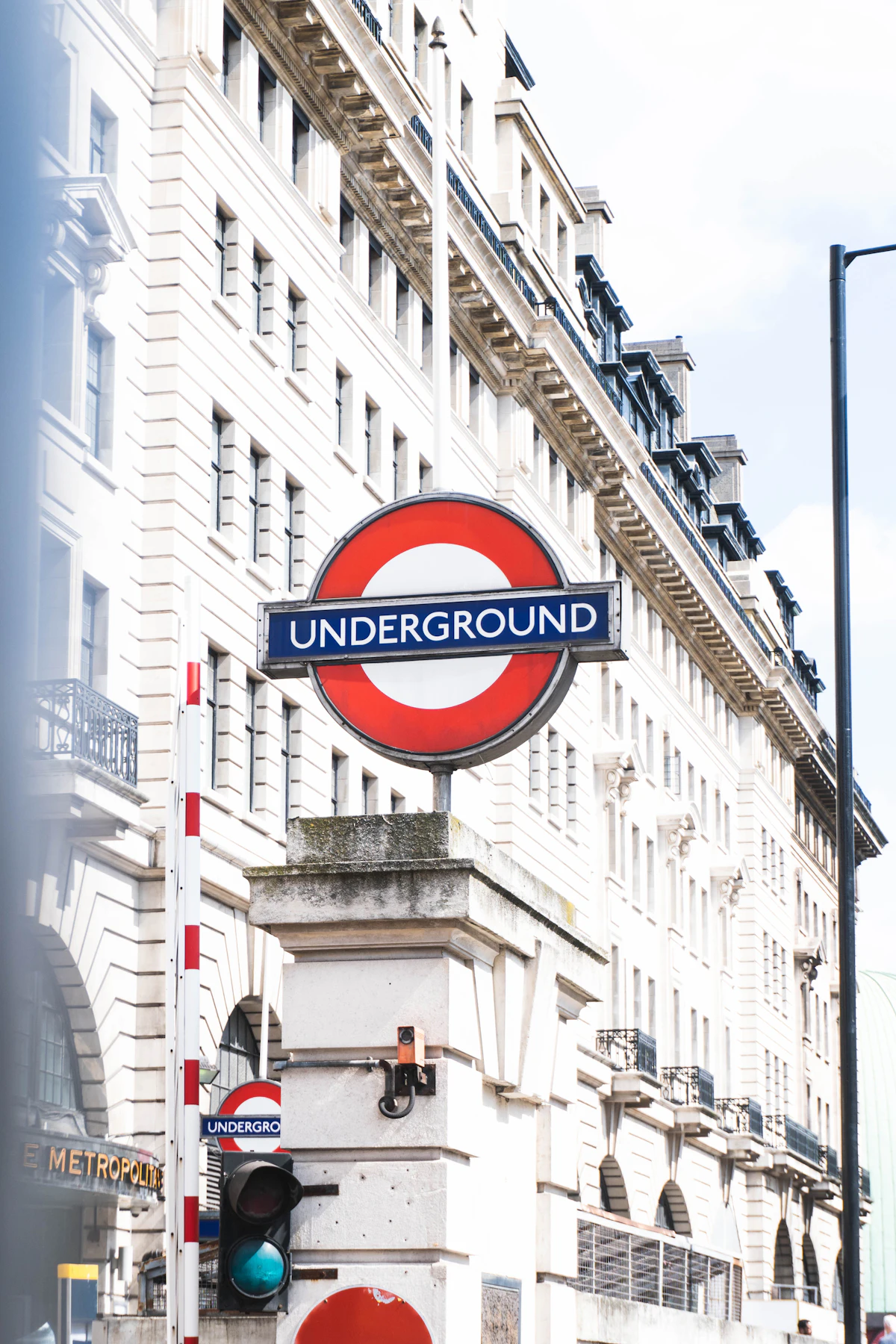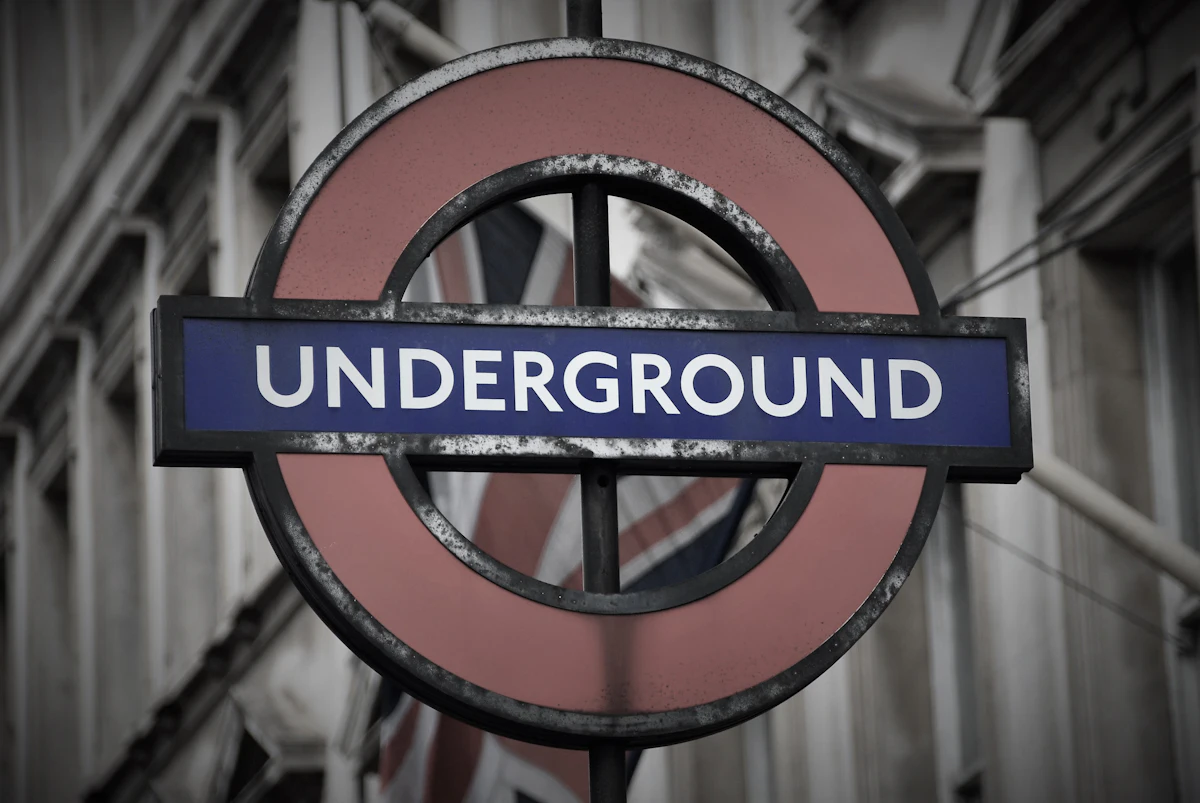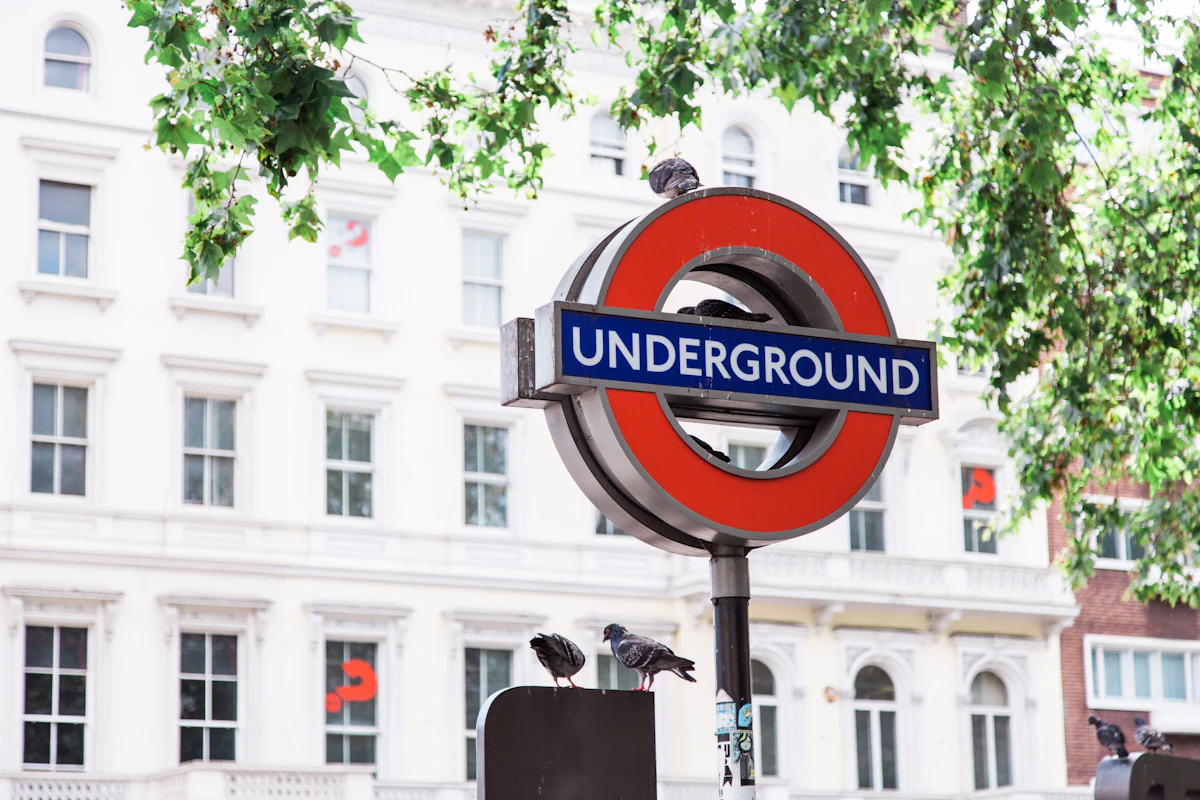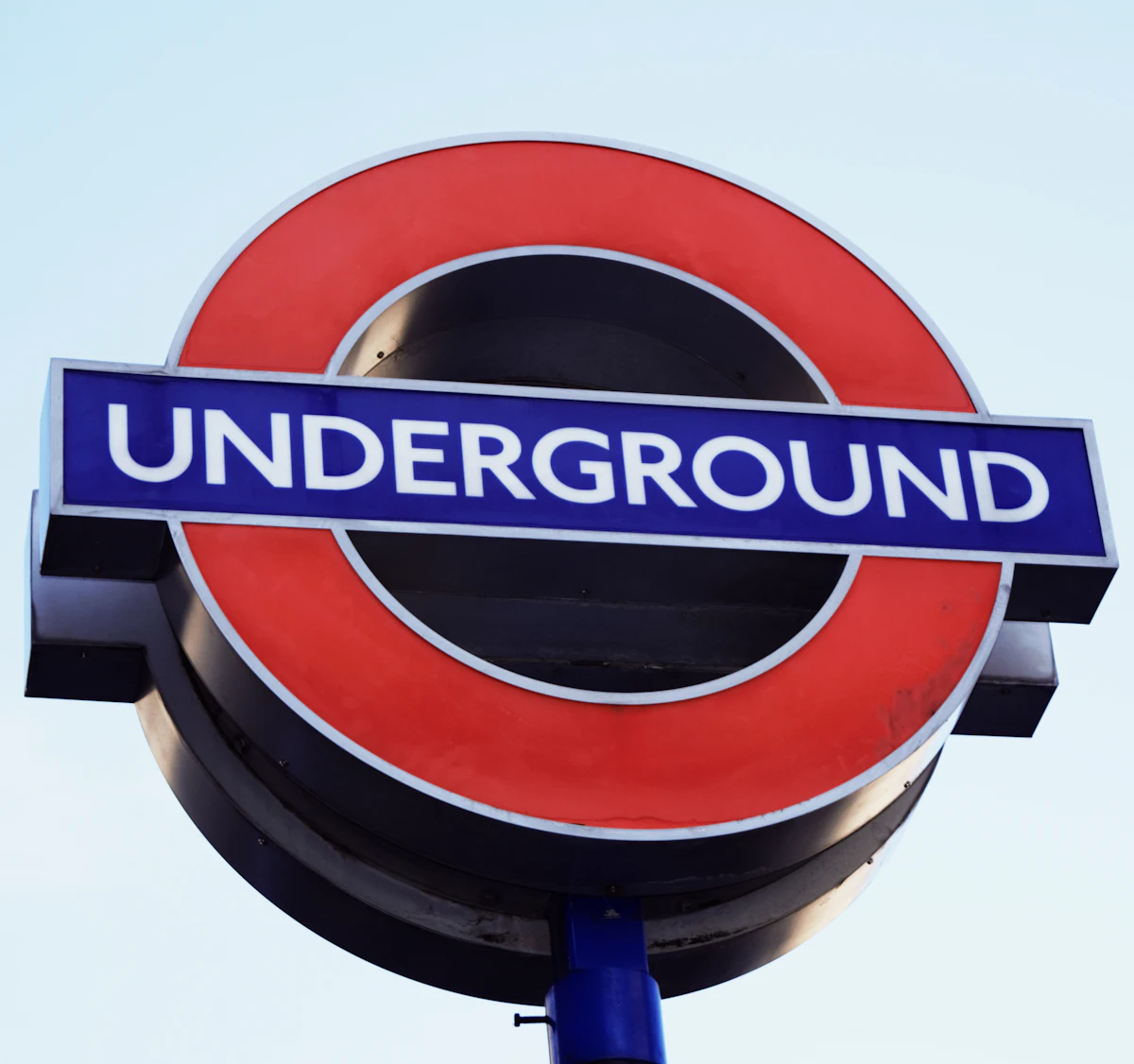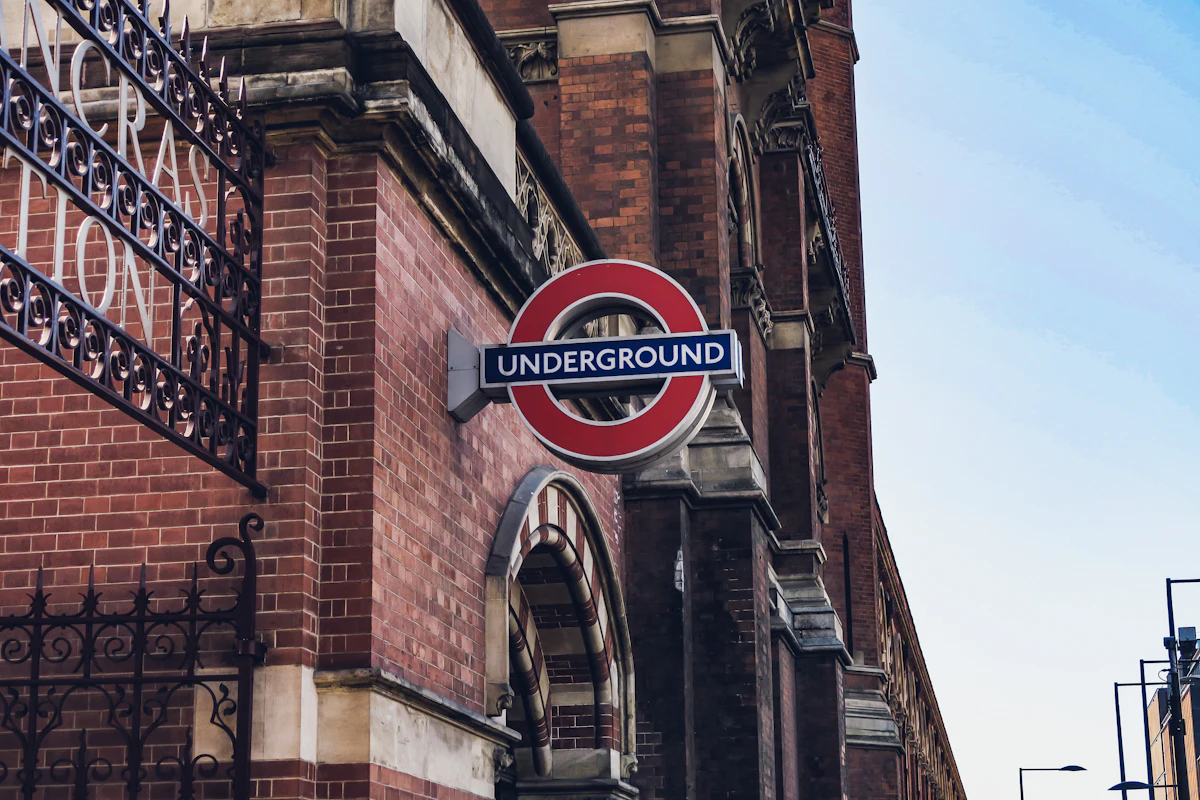
บนชานชาลาที่มีคนยืนรออยู่เต็ม สายตาที่เหลือบขึ้นไปมองป้ายชื่อสถานีมักไม่ทันสังเกตอะไร นอกจากว่าตัวเองอยู่ตรงไหน แต่ถ้ามองนานอีกนิด จุดเล็กๆ บนตัว i จะไม่ใช่วงกลม มันเป็นสี่เหลี่ยมข้าวหลามตัด และจุดนั้นเองที่ทำให้ตัวอักษรทั้งชุดเป็นของลอนดอน
ป้ายวงกลมสีแดงขาวของ London Underground กับตัวอักษรฟอนต์ Johnston
ฟอนต์ Johnston คือตัวอักษรที่ Edward Johnston ออกแบบให้กับรถไฟใต้ดินลอนดอน เรื่องเริ่มในปี 1913 เมื่อ Frank Pick ผู้จัดการฝ่ายการค้าของบริษัทรถไฟใต้ดินในเวลานั้น ต้องการสร้างภาพจำที่ชัดเจนให้ระบบขนส่งของเมือง เขาจึงมอบโจทย์ให้ Johnston ทำตัวอักษรที่มีความเรียบง่ายอย่างหนักแน่น มีรากอยู่ในประเพณี แต่เป็นของศตวรรษที่ยี่สิบอย่างเต็มตัว
Johnston ไม่ใช่นักออกแบบตัวพิมพ์แบบที่เราคุ้น เขาเป็นนักเขียนอักษรวิจิตรและครูสอนคัดลายมือ ลูกศิษย์ของเขาคนหนึ่งคือ Eric Gill ที่ต่อมาทำฟอนต์ Gill Sans สายตาแบบช่างคัดลายมือนี้ติดมากับงาน สัดส่วนของตัวอักษรถูกวางจากรอยพู่กันปลายตัดที่ให้เส้นรูปสี่เหลี่ยมข้าวหลามตัด ซึ่งกลับมาปรากฏเป็นจุดบนตัว i และ j อีกครั้ง
ป้ายชื่อสถานีรถไฟใต้ดินลอนดอนที่ใช้ตัวอักษร Johnston
สิ่งที่ทำให้ Johnston พิเศษในยุคนั้นคือมันเป็นซานเซอริฟที่มีมนุษยธรรม ไม่ใช่ตัวอักษรเรขาคณิตเย็นชา แต่มีจังหวะของมือคนอยู่ในเส้น ในช่วงเวลาที่ป้ายส่วนใหญ่ยังใช้ตัวอักษรมีเชิงที่ประดับประดา การเลือกทำตัวอักษรเปลือยเปล่าไร้เชิงเพื่อการอ่านที่เร็วและชัด ถือเป็นการตัดสินใจที่ก้าวหน้ามาก
เสาป้าย Underground รูปทรงคลาสสิกกับตัวอักษร Johnston
Johnston วาดตัวอักษรไว้เพียงน้ำหนักเดียว แต่มันถูกใช้ซ้ำในทุกจุดของระบบ ตั้งแต่ป้ายชื่อสถานี แผนที่ ป้ายบอกทาง ไปจนถึงวงกลมสีแดงคาดแถบน้ำเงินที่กลายเป็นสัญลักษณ์ของเมือง ตัวอักษรกับวงกลมนั้นทำงานด้วยกันมานานจนแยกจากกันแทบไม่ออก คนเห็นแล้วรู้ทันทีว่าคือรถไฟใต้ดินลอนดอน
ป้ายวงกลม Underground สีแดงดำริมถนนกรุงลอนดอน
ตัวอักษรที่ทำหน้าที่บนป้ายทุกวันแบบนี้ มีความใกล้เคียงกับงานเขียนป้ายด้วยมืออยู่ไม่น้อย ทั้งคู่เกิดจากคนที่คิดเรื่องการอ่านในพื้นที่จริง ไม่ใช่ตัวอักษรบนหน้ากระดาษที่นิ่งอยู่กับที่ แต่เป็นตัวอักษรที่ต้องอ่านออกในระยะไกล ในแสงน้อย และในจังหวะที่คนกำลังรีบ
ป้าย Underground แถบสีน้ำเงินบนวงกลมแดงกับคำว่า Underground
เวลาผ่านไปกว่าร้อยปี ตัวอักษรก็ต้องปรับตัว ในปี 2016 บริษัท Monotype ได้รับมอบหมายให้ทบทวนฟอนต์นี้อีกครั้ง ทีมออกแบบปรับรายละเอียดให้เข้ากับยุคดิจิทัล และเพิ่มน้ำหนักบางพิเศษสองแบบสำหรับหน้าจอ ผลลัพธ์คือ Johnston100 ที่ใช้กันมาตั้งแต่นั้น ยังคงเค้าเดิมของงานปี 1916 ไว้ พร้อมกับตอบโจทย์ที่ Johnston ไม่เคยต้องเจอ
ป้ายบอกทางบนชานชาลารถไฟใต้ดินลอนดอนด้วยฟอนต์ Johnston
ตัวอักษรที่ดีที่สุดบางชุดอาจเป็นตัวที่เราไม่เคยหยุดชม เพราะมันยุ่งอยู่กับการทำงาน จุดสี่เหลี่ยมเล็กๆ บนตัว i ที่ผ่านตาคนหลายล้านคนทุกวัน ยังคงบอกทางเงียบๆ อยู่ตรงนั้น รอให้ใครสักคนเงยหน้าขึ้นมองนานพอจะเห็นมัน